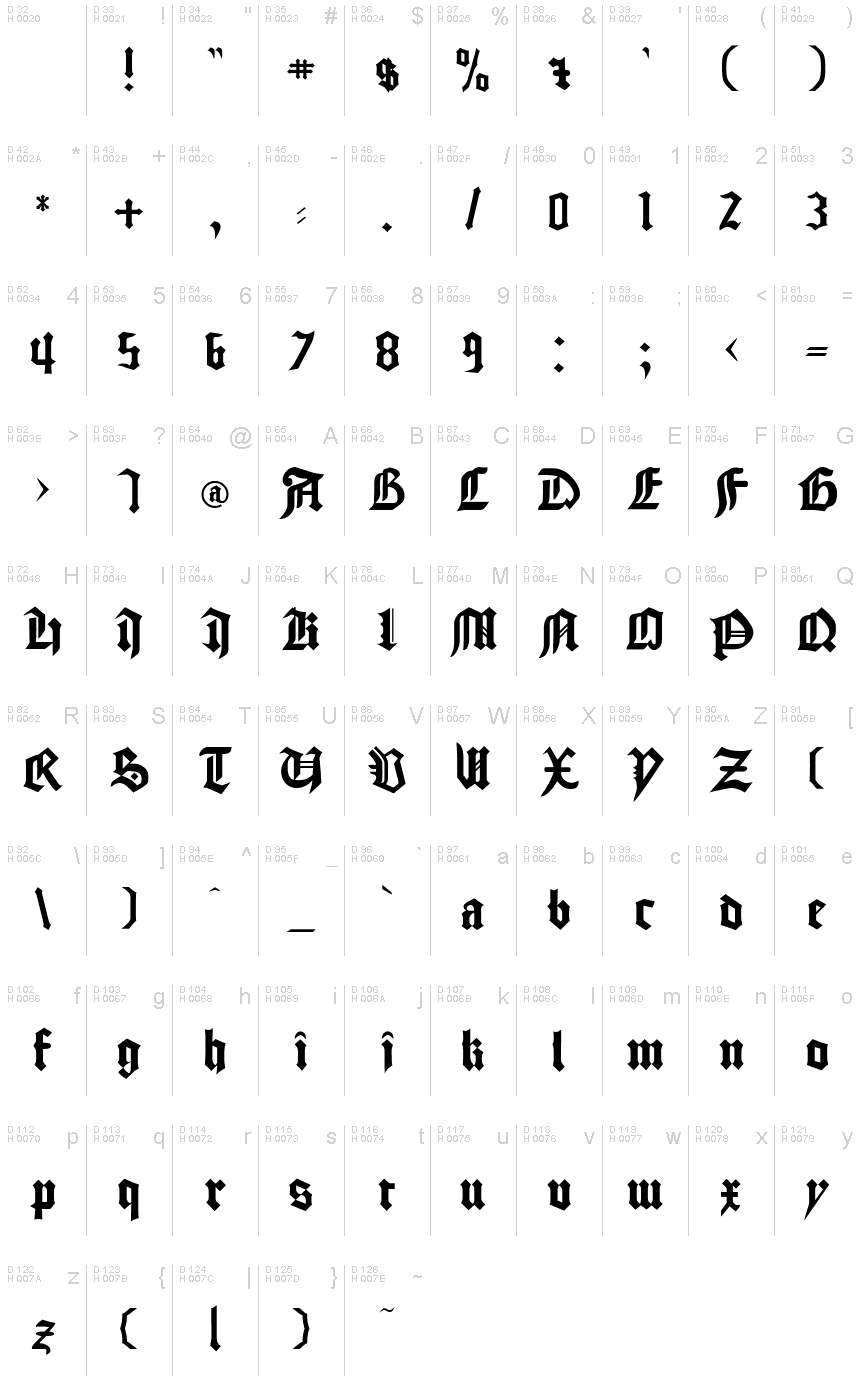
Good City Modern Plain od A.S. Meit to darmowy gotycki krój pisma, który przenosi Twoje projekty prosto w epokę iluminowanych rękopisów. Gęste, nasycone tuszem kreski oraz strome, ciosane łuki przywodzą na myśl początki drukarstwa, nadając nagłówkom pełną powagi, ceremonialną formę. Rytm jest ciasny i zwarty, dzięki czemu każde słowo sprawia wrażenie wyrytego w kamiennym nadprożu lub odbitego z ciężkiej metalowej czcionki.
Good City Modern Plain sprawdzi się przy brandingu browaru rzemieślniczego, logo zespołu metalowego, okładkach książek dark fantasy, plakatach muzealnych czy oprawie graficznej turniejów i festiwali. Ten darmowy font błyszczy użyty w dużym rozmiarze w nazwach i tytułach; w tekście głównym połącz go z nowoczesnym bezszeryfowym krojem, aby historyczna faktura pozostała efektowna i czytelna.